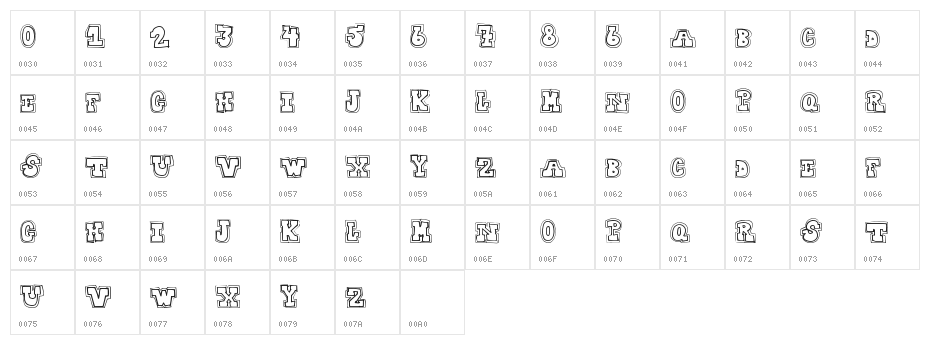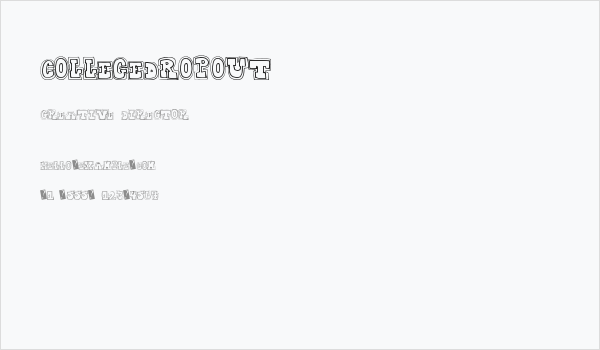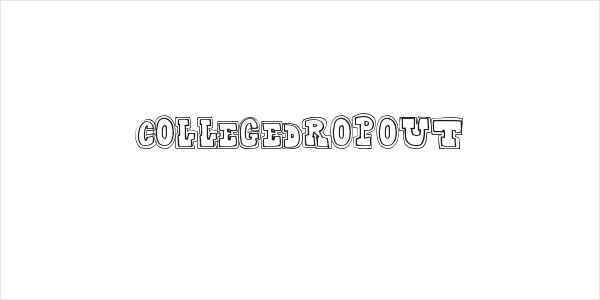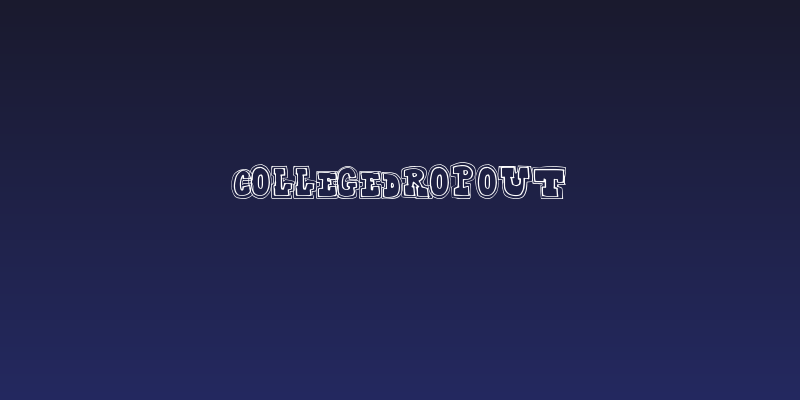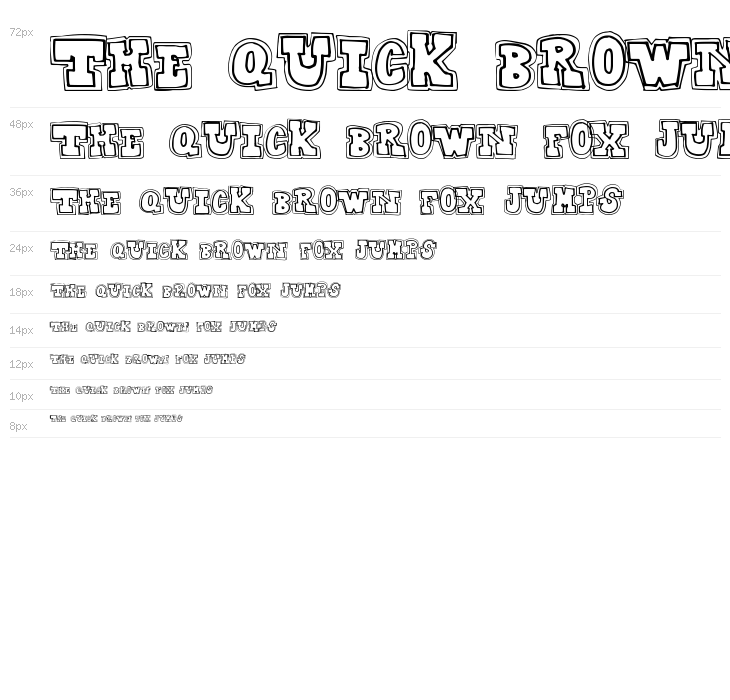
CollegeDropout Font
| Stile generale | Playful, Energetic, Comic |
| Caso d'uso | Headlines, Posters, Logos |
| Progetti proposti | Ideal for comic book titles, children's book covers, playful posters, and event flyers. |